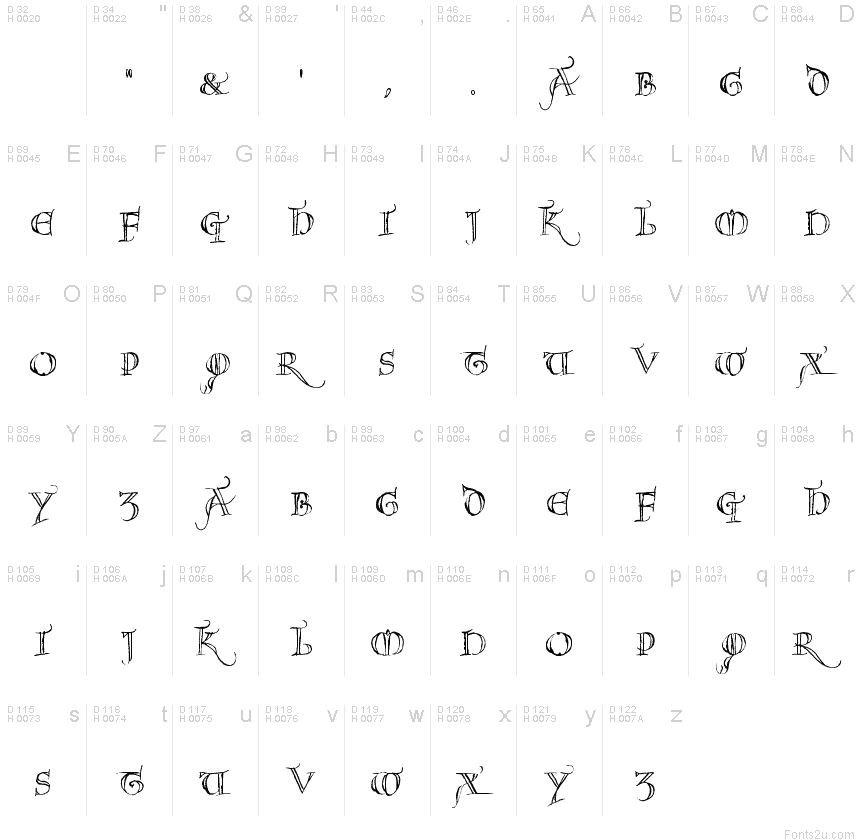
Noel, il carattere gratuito in maiuscolo medievale gotico di Ethan Dunham per Fonthead Design, ha l'aspetto aereo e scritto a mano delle lettere dei manoscritti, impreziosito da volute intrecciate. Le lettere poggiano su tratti verticali alti, curve arrotondate e piccole finiture a uncino, ma ciò che definisce davvero l'alfabeto è il contrasto tra la struttura essenziale e quei riccioli filiformi che lo rendono cerimonioso piuttosto che pesante.
Questo font gratuito è perfetto per biglietti di Natale, bollettini parrocchiali, locandine stagionali, etichette per regali, copertine di libri e titoli, dove una riga breve può esibire i suoi ornamenti senza affollare la pagina. Funziona bene anche per iniziali e monogrammi, poiché le maiuscole hanno abbastanza curve e slancio per risultare complete anche da sole.